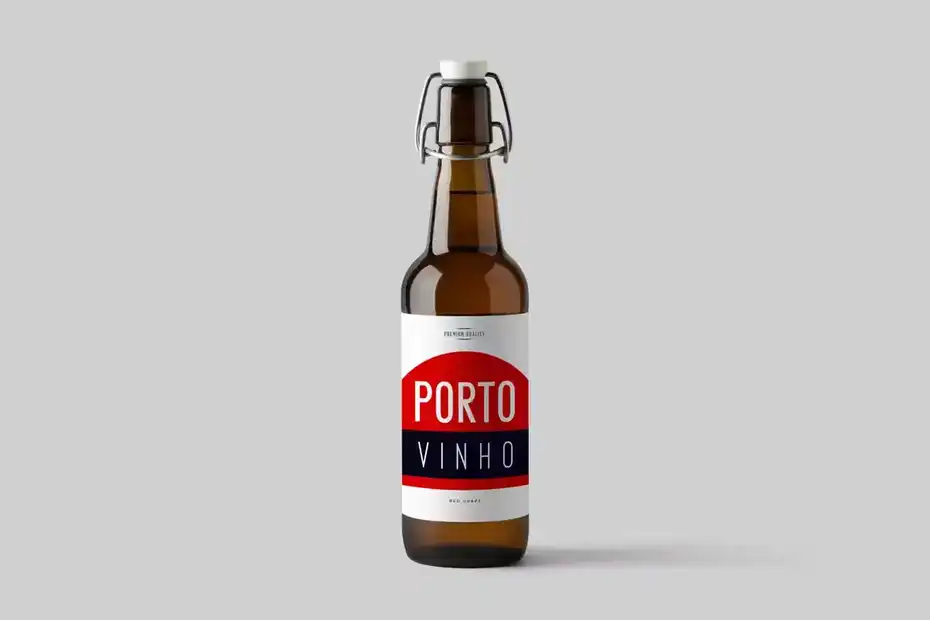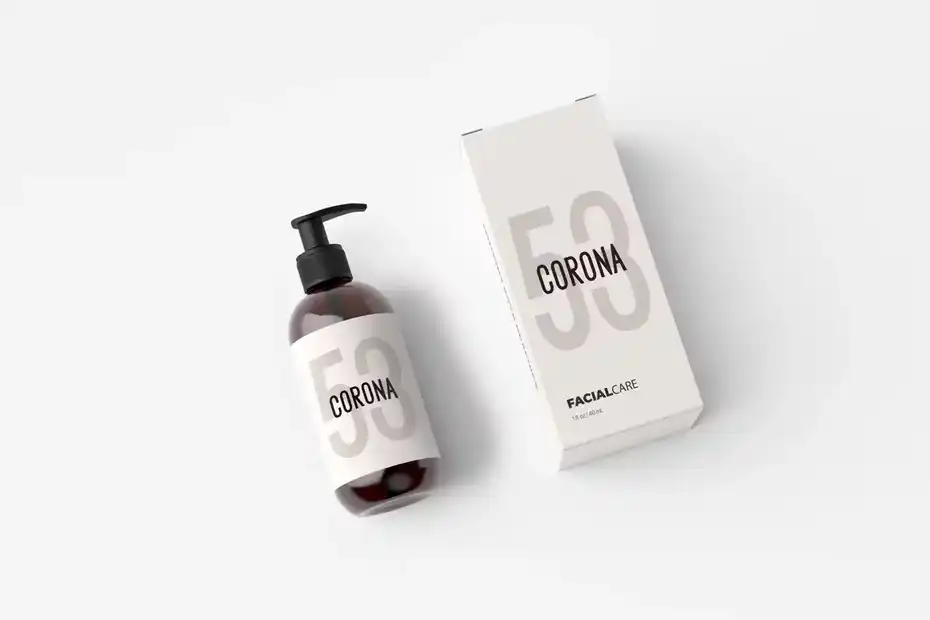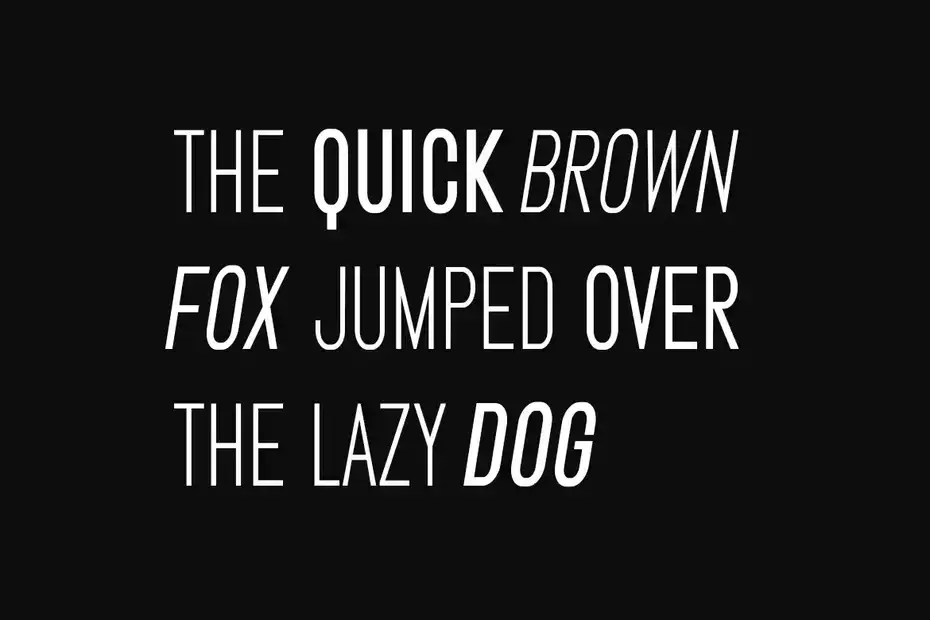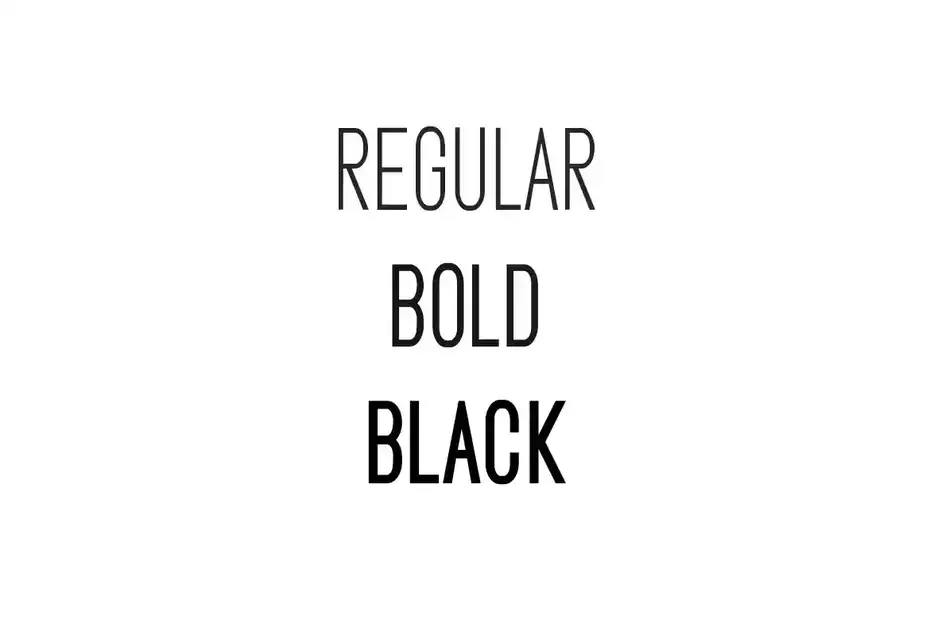
دانلود فونت مدرن برای تیتر و لوگو STARK – Modern Display / Headline / Logo Typeface
دانلود فونت مدرن برای تیتر و لوگو STARK : این مجموعه شامل یک فونت انگلیسی مدرن است که برای لوگو، برندینگ، سرفصل، تیتر و غیره مناسب میباشد.
• عنوان مجموعه: STARK – Modern Display / Headline / Logo Typeface
• فضا بین حروف: معمولی، متراکم، با فاصله